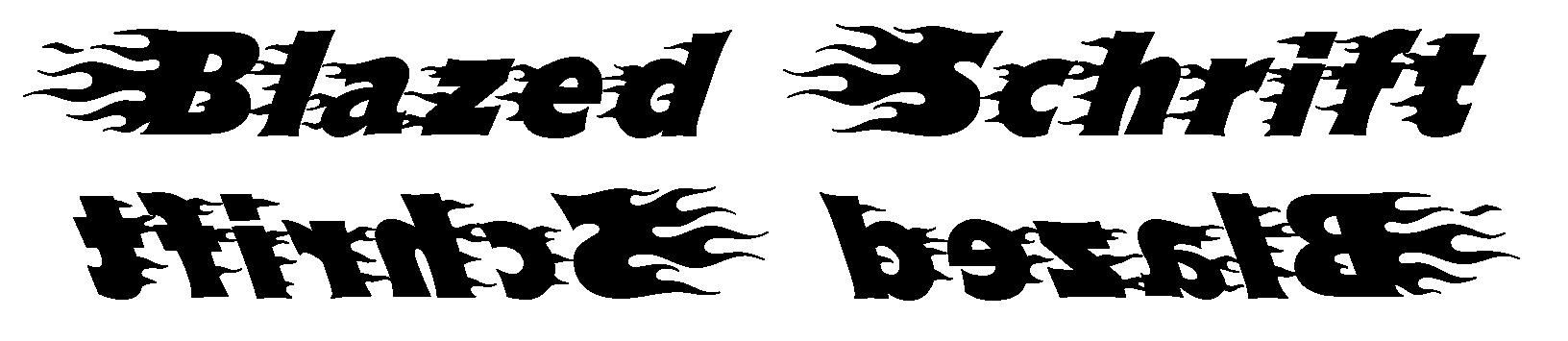
Suche Flammenschrift
Ich suche eine Flammen-Schrift, wo die Flammen einmal nach links und einmal nach rechts zeigen, bei gleicher Schriftart.
So ungefähr wie auf dem Bild, nur nicht spiegelverkehrt. Könnt ihr mir vielleicht helfen.